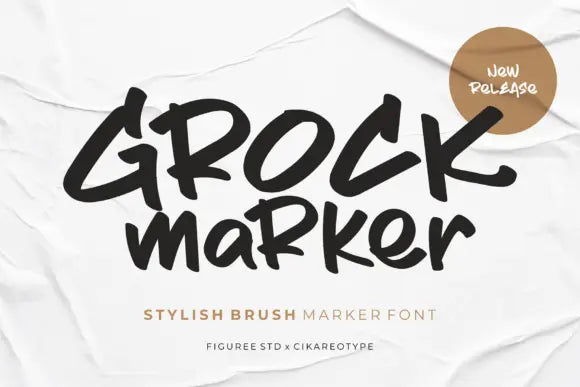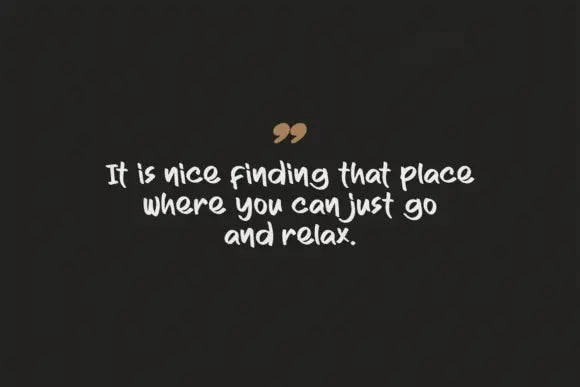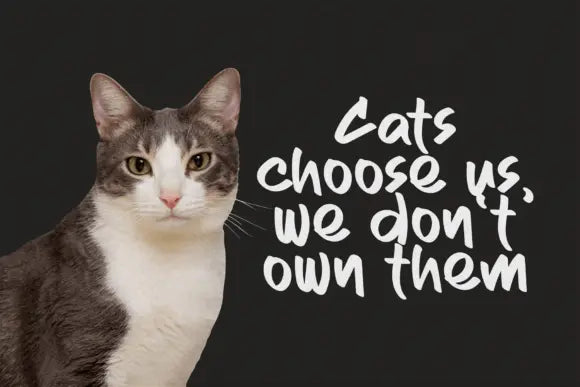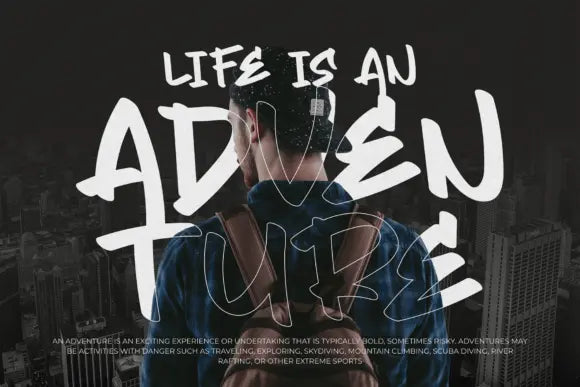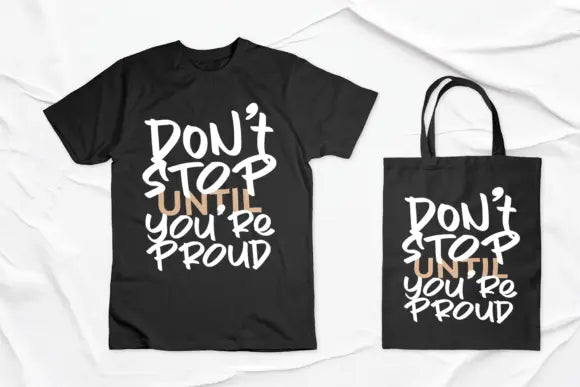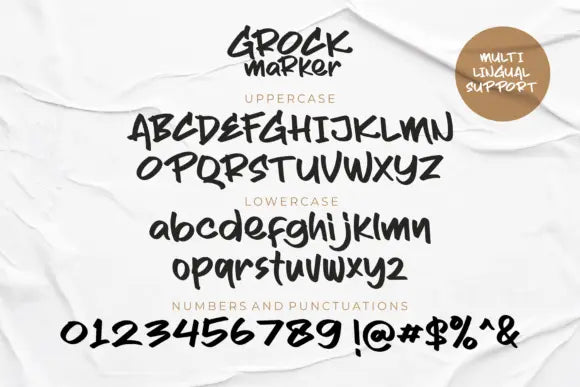
Fuente Grock Marker
Grock Marker es una elegante fuente de marcador de pincel. Hecho en combinación con letras a mano, viene con un movimiento dramático y es ideal para cualquier próximo proyecto creativo que necesite un toque natural y escrito a mano.
Es ideal para logotipos, citas escritas a mano, empaques de productos, encabezados, carteles, mercancías, redes sociales y tarjetas de felicitación.